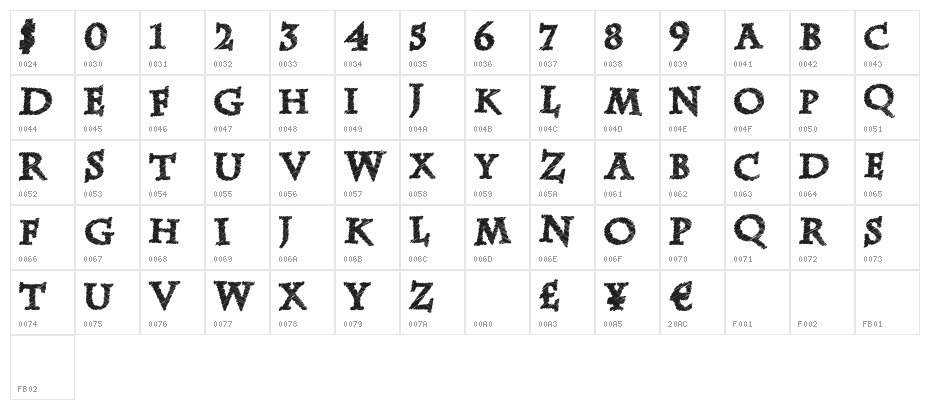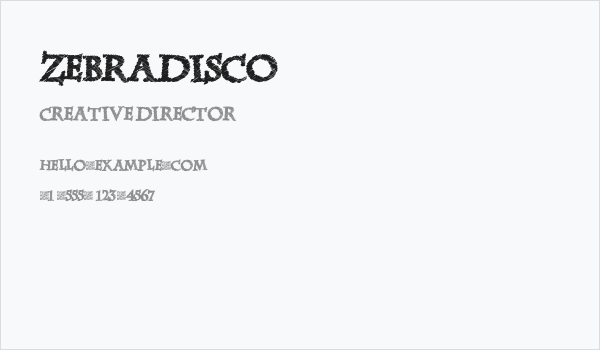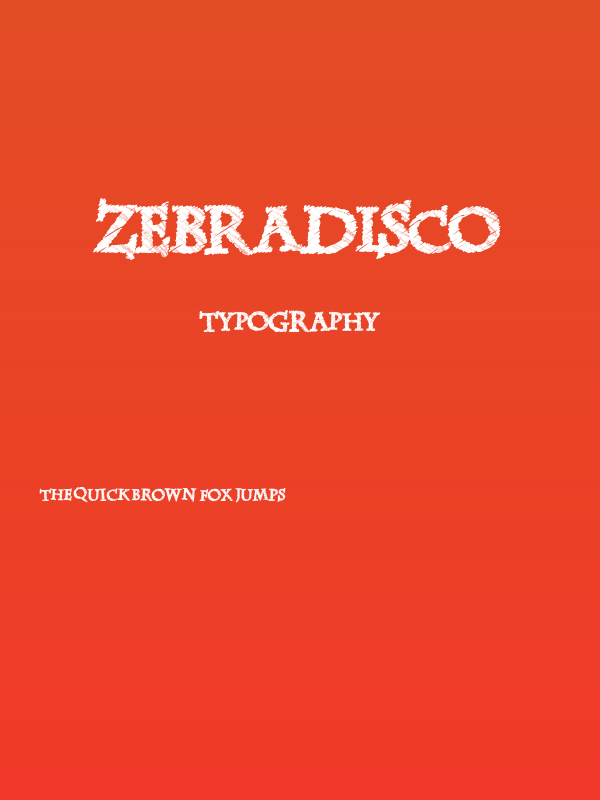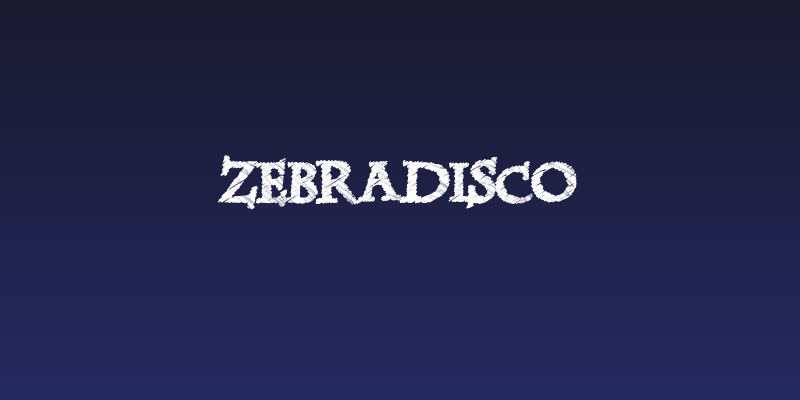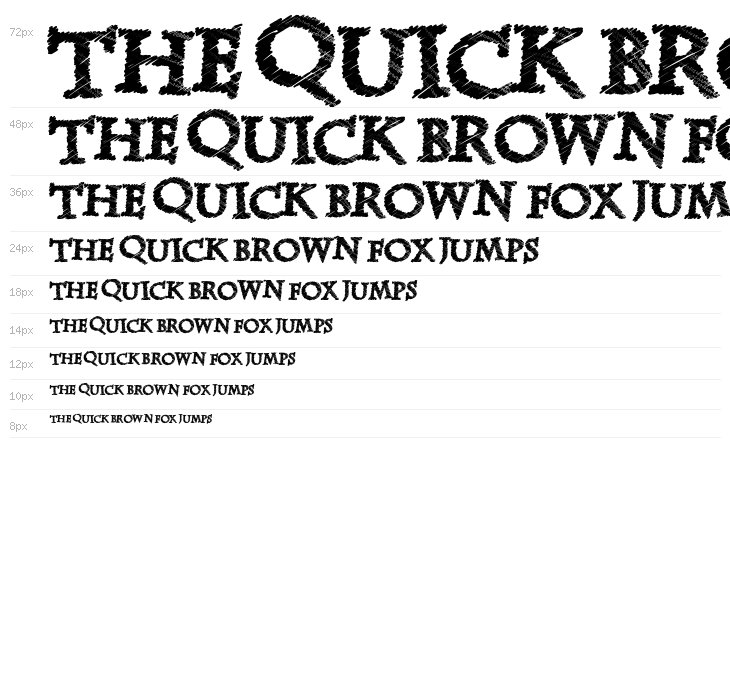
ZebraDisco Font
✎ Distorted Eroded
| الفئات | Distorted Eroded |
| العرض | Condensed |
| مشاريع مقترحة | Ideal for posters, album covers, event flyers, and branding materials that require a bold and artistic touch. |